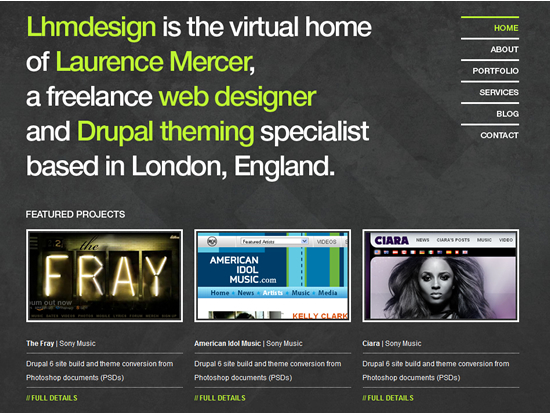
Selección de 20 sitios Web con bonitas tipografías
"La tipografía (del griego τύπος typos, golpe o huella, y γράφω graphο, escribir) es el arte y técnica del manejo y selección de tipos, originalmente de plomo, para crear trabajos de impresión".El tipógrafo Stanley Morrison la definió como: El manejar correctamente la tipografía no es nada sencillo, implica la selección de tipos de letra, tamaño de punto, longitud de la línea, espacio entre líneas, la adaptación de los espacios entre grupos de letras y ajustar el espacio entre pares de letras (kerning). La tipografía ha desempeñando y desempeña un importante papel en diferentes tipos de medios como la publicación, el envasado, la televisión, etc. Resumiendo, es la manera de presentar la información a nuestra audiencia en forma de texto. Una buena tipografía puede ser agradable a la vista y fácil de leer. Teniendo esto en cuenta en Queness, comparten el artículo 20 Websites with Beautiful Typography, donde han selecionado 20 sitios web con una selcción y composición tipografía realmente hermosa, creo que esta será una buena inspiración para todos nosotros. Espero que lo disfrutéis. Escrito por Toni Comparte este artículo: Estas son las categorías a las que pertenece el artículo Selección de 20 sitios Web con bonitas tipografías: